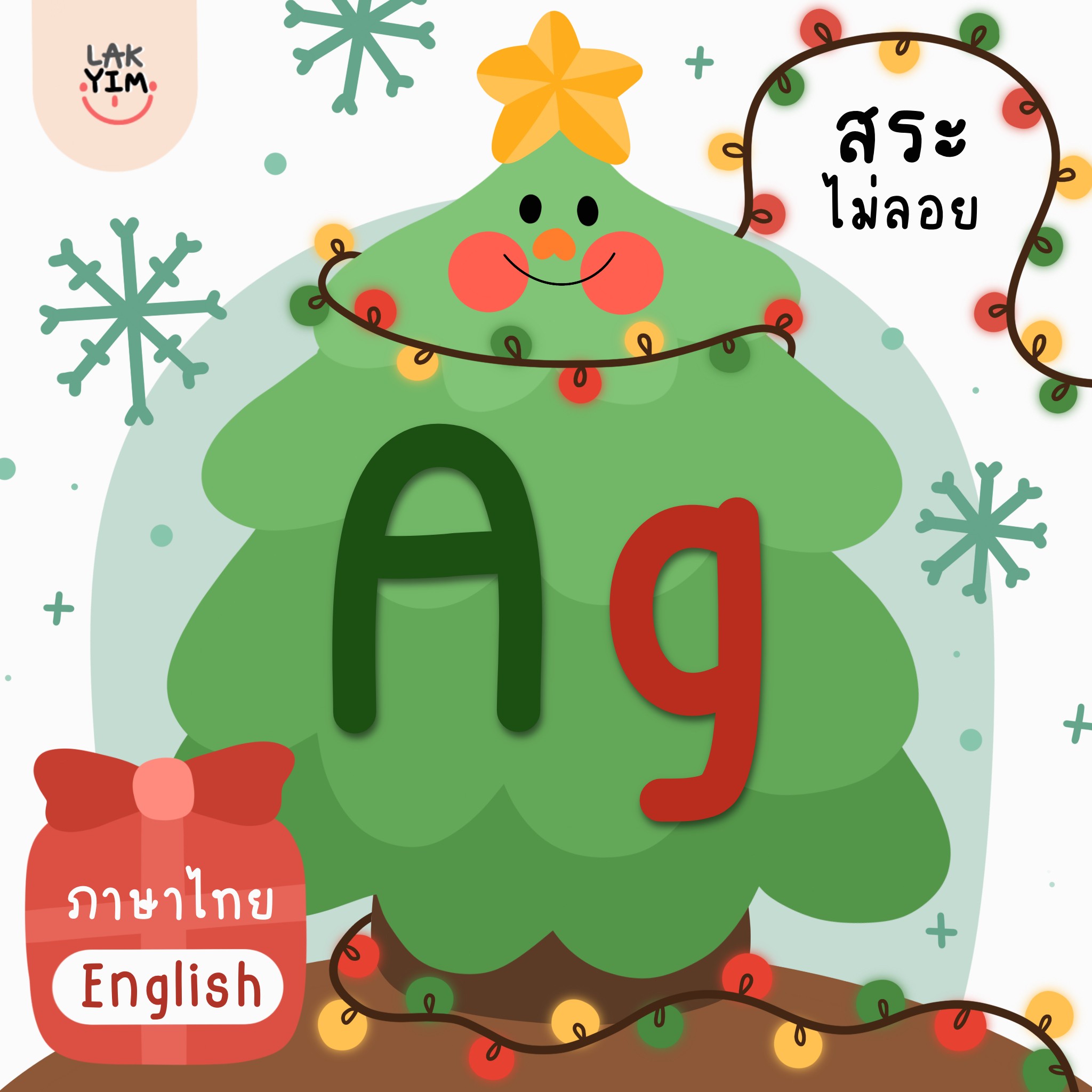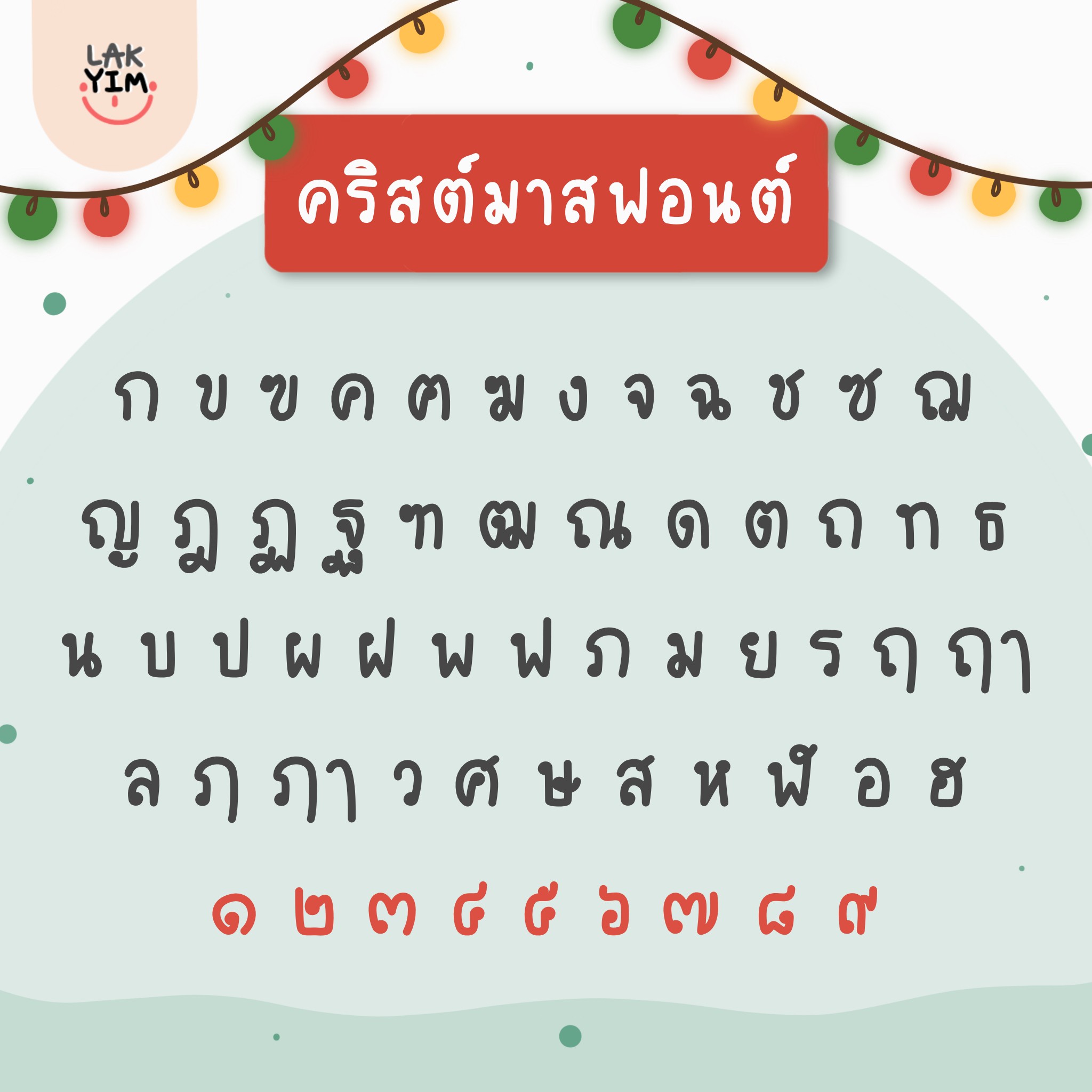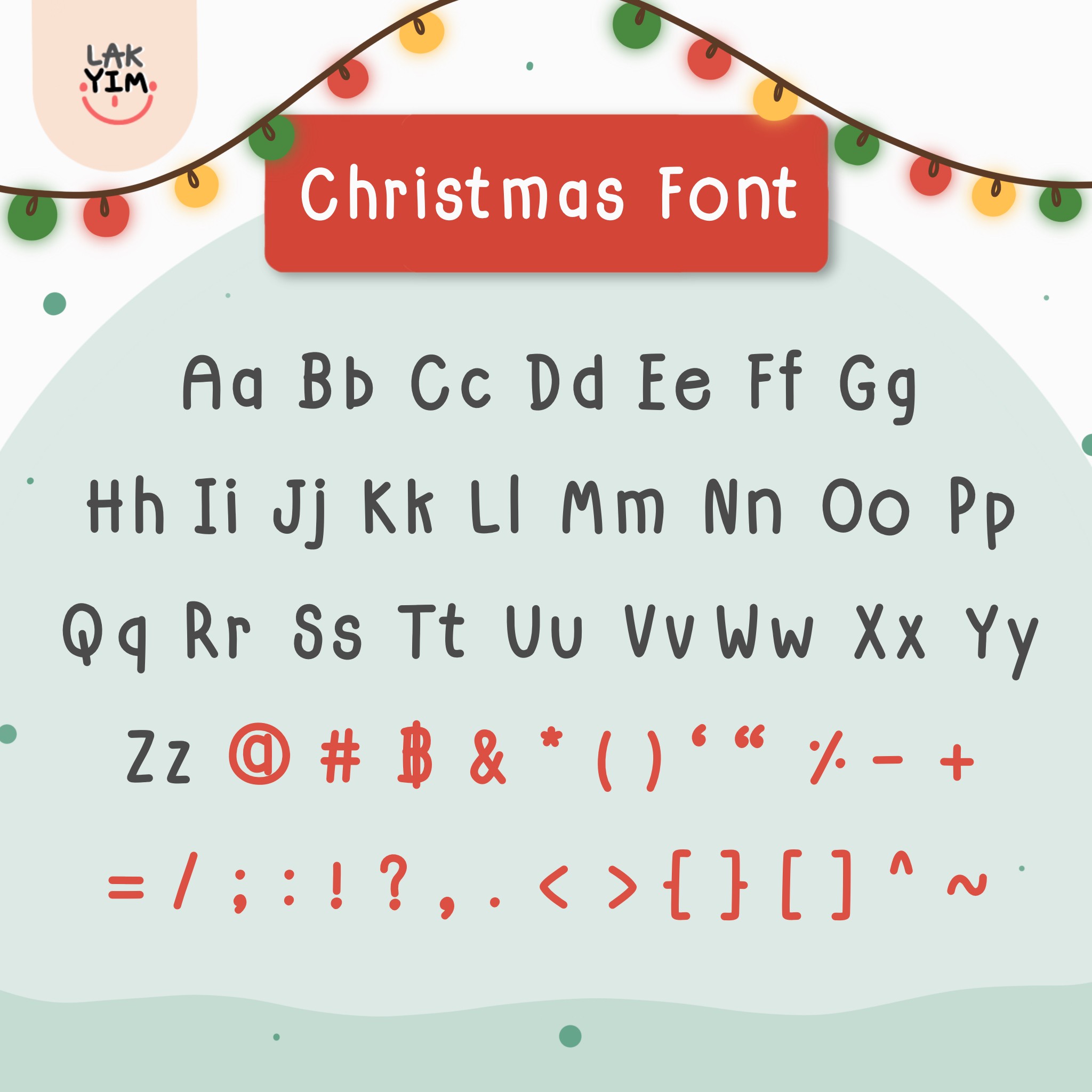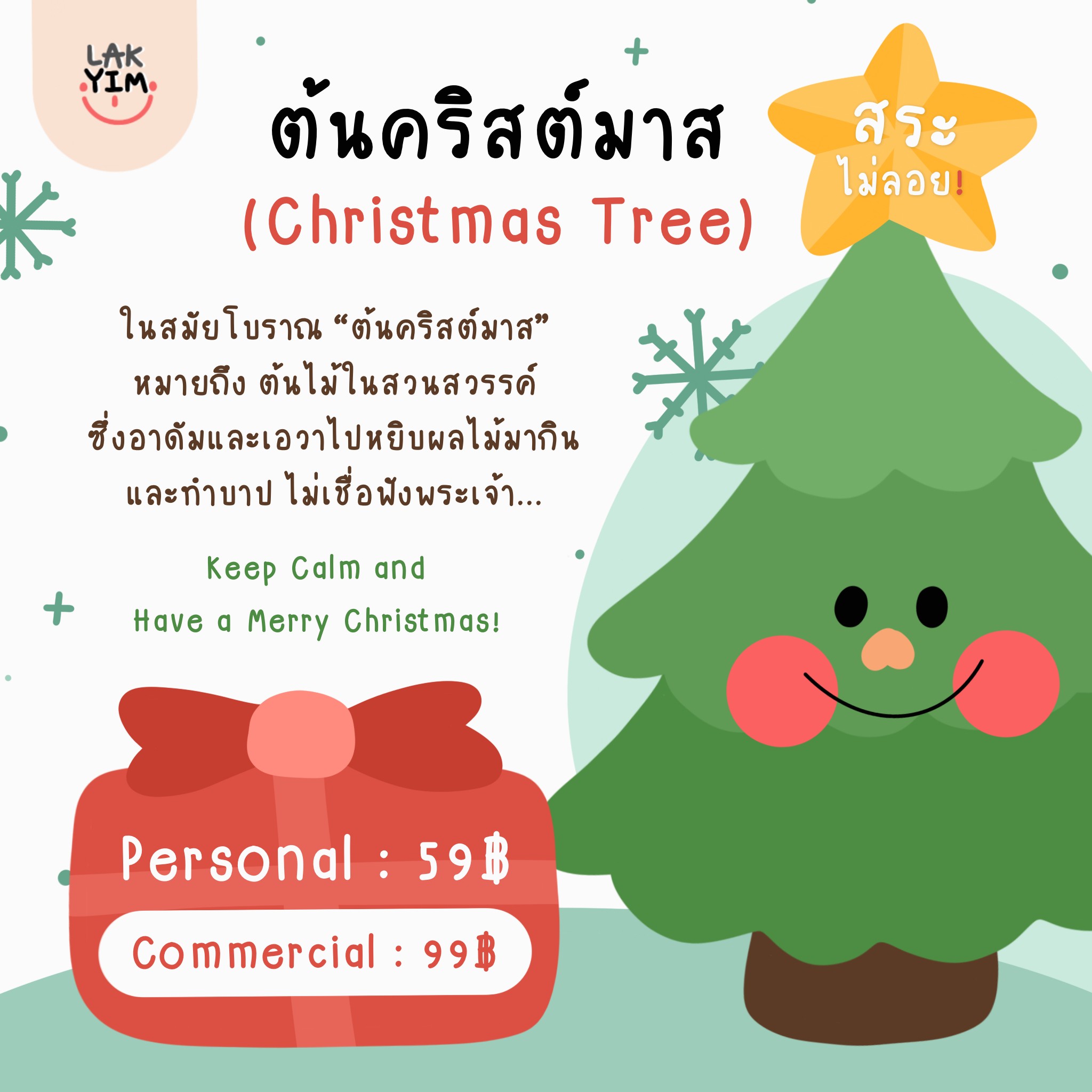
CHRISTMAS FONT
ชื่อสินค้า : CHRISTMAS FONT 🎄❤️
รายะเอียดภาษาไทย:
ฟอนต์ลายมือแบบตัวบางหนา มีความน่ารักอบอุ่นเข้ากับเทศกาลคริสต์มาสมาก ๆ
ทั้งยังอ่านง่าย สบายตา เหมาะกับการเอาไปใช้เขียนบันทึก หรือทำชีทสรุป 🗒️✨
📍ที่สำคัญ: สระ ไม่ ลอย ‼️‼️
– มีทั้งภาษาไทยและภาษาอังกฤษ
รายละเอียดภาษาอังกฤษ:
Handwritten font, There is a very cute and warm Christmas season.
It’s also easy to read, comfortable on the eyes, suitable for writing notes. Or make a summary sheet 🗒️✨
– available in both Thai and English